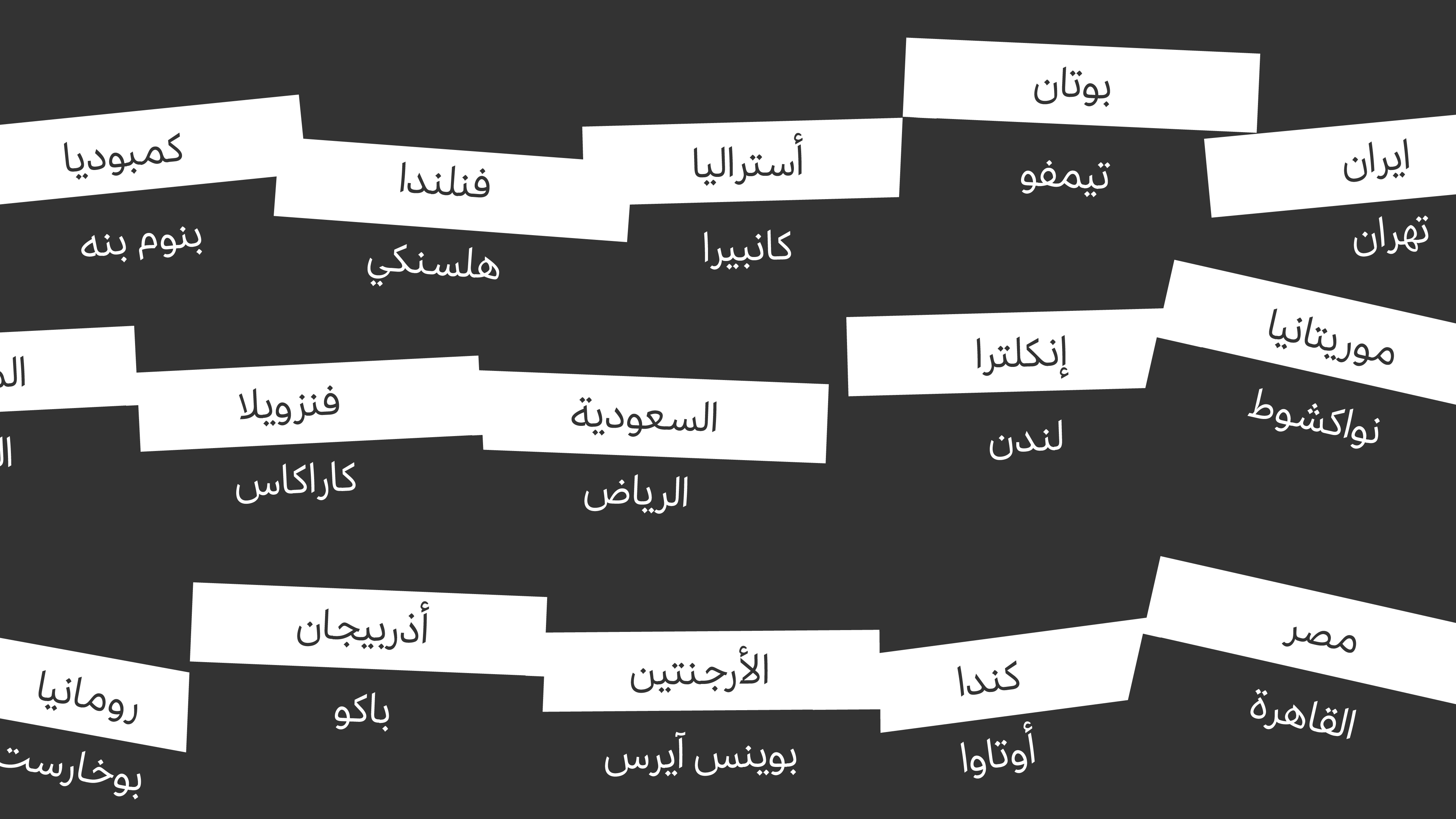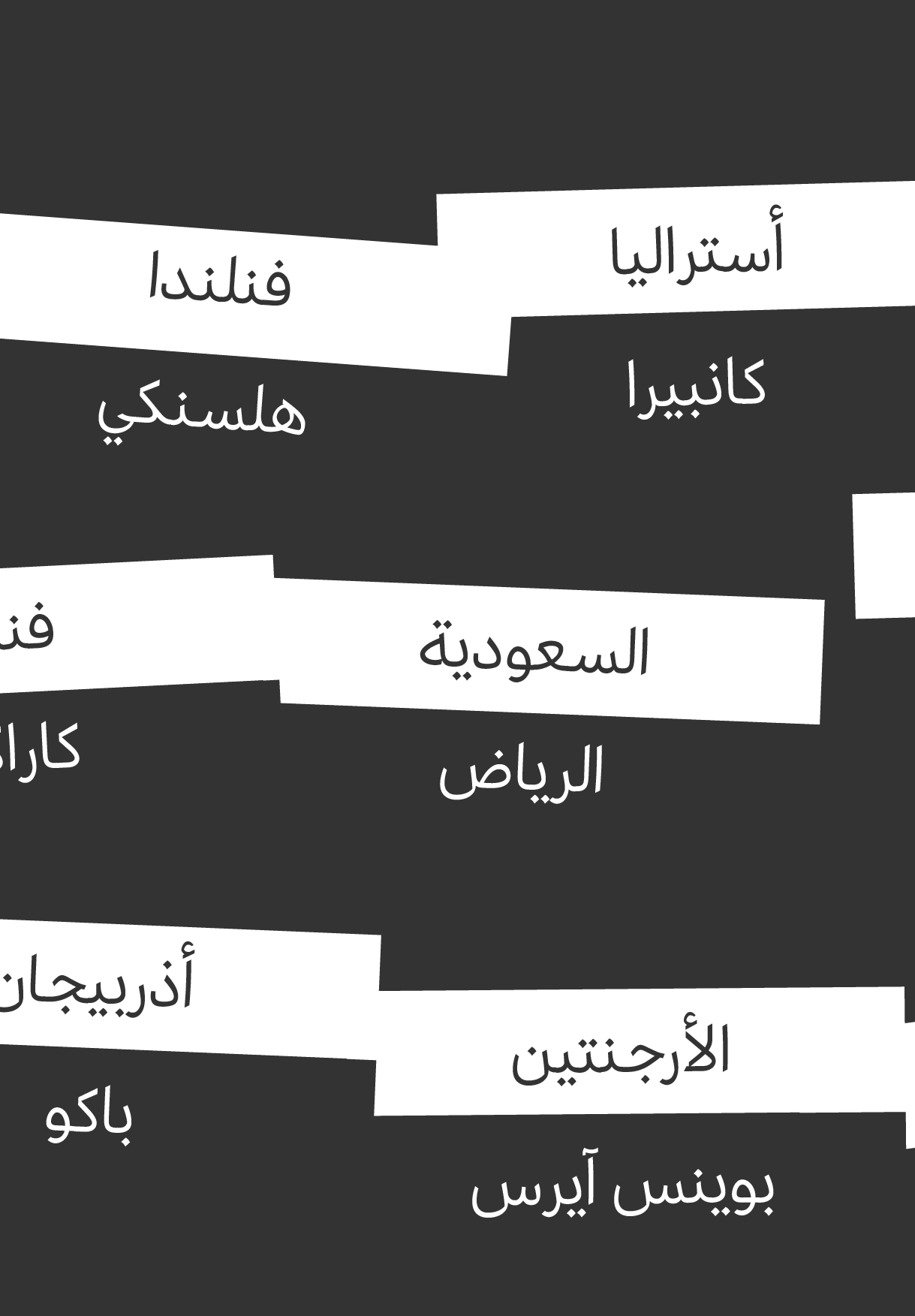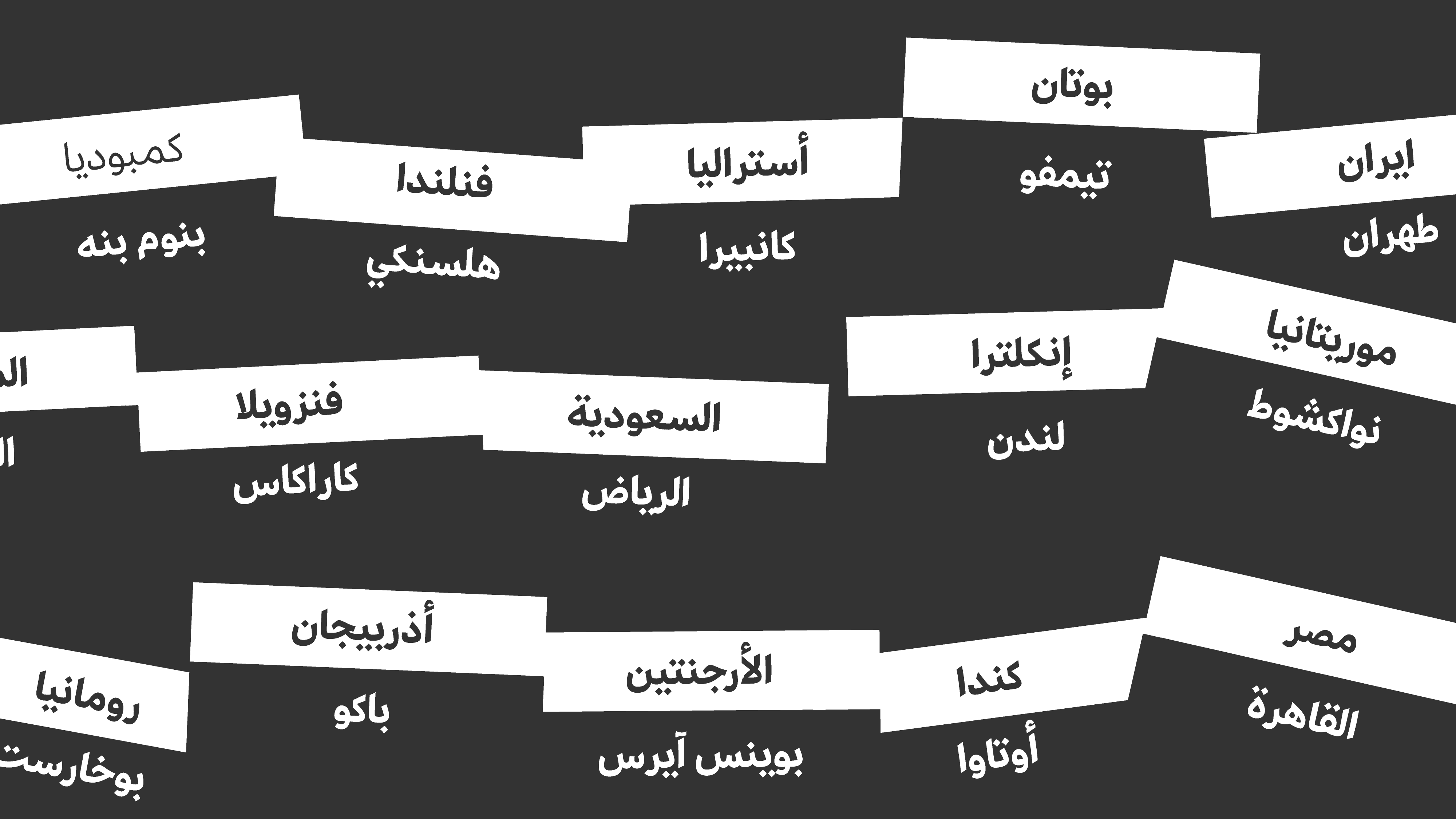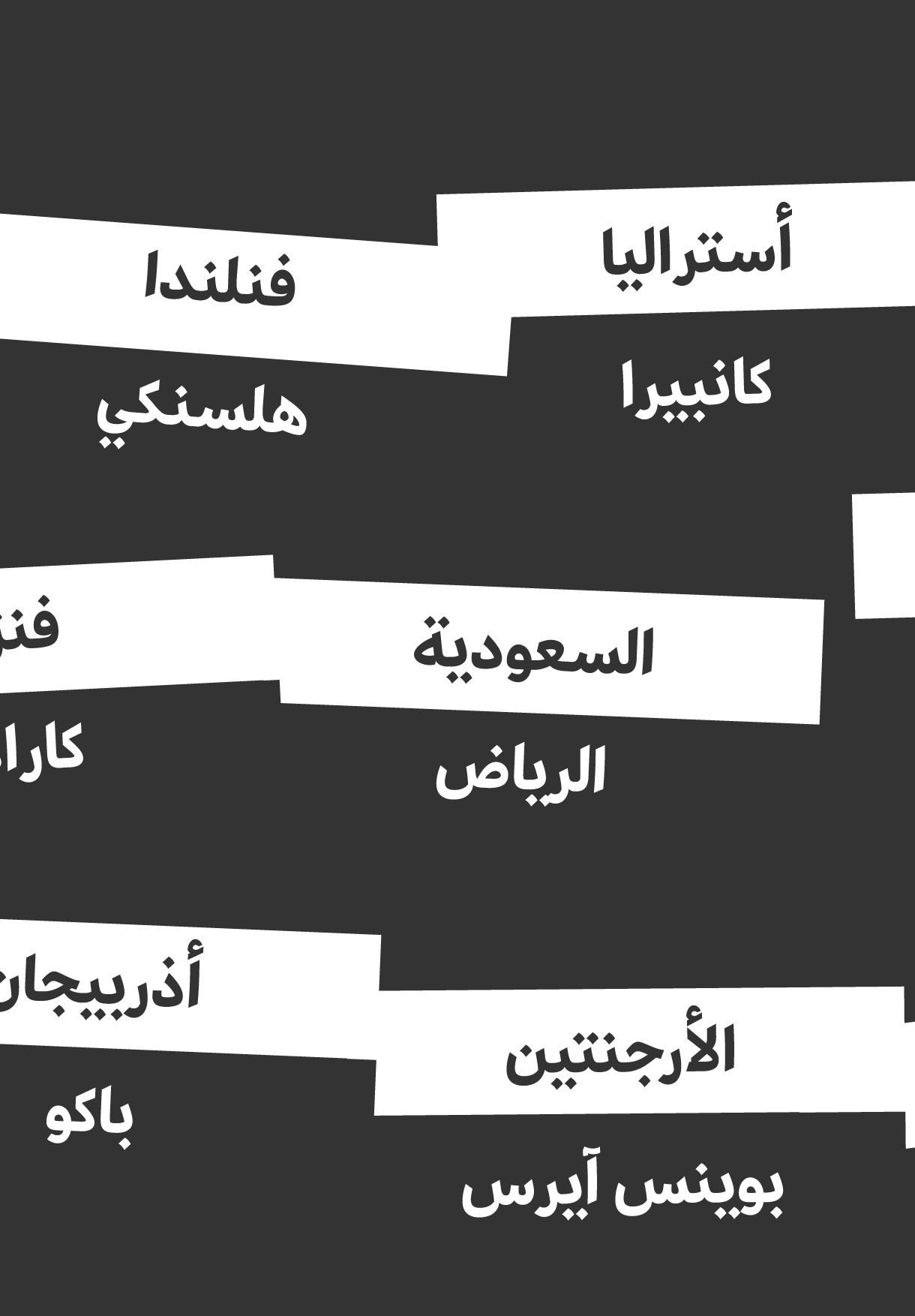
F37 Hooj Arabic Font Sampler
F37 Hooj به تایپ جاودانه Futura‌ با طراحی Paul Renne، و همچنین به دیگر فونت‌های سنس معروف آلمانی مانند Erbar، Kabel و Super Grotesk ادای احترام می‌کند. F37 Hooj به تایپ جاودانه فوتورا با طراحی پُل رنه، و همچنین به دیگر فونت‌های سنس معروف آلمانی مانند اِربار، کابِل و سوپر گروتسک ادای احترام می‌کند.